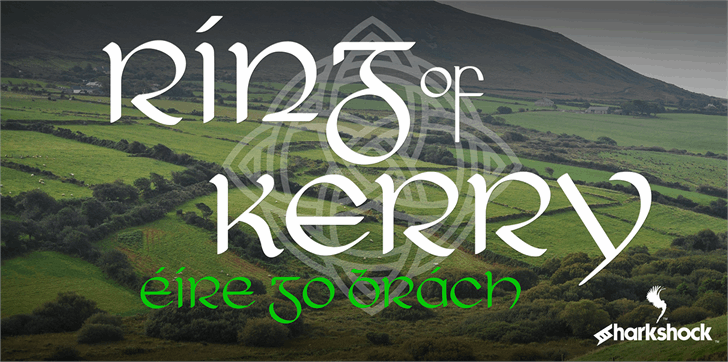
Ring of Kerry Font
A Ring of Kerry é uma fonte display vibrante criada pelo designer Hamilton, disponível tanto em formato OTF quanto TTF. Nascida em 2016, essa fonte exibe um toque alegre e dinâmico que encaixa-se perfeitamente para aplicativos de design gráfico como logotipos e publicações. Com uma paleta de cores vivas e detalhes impressionantes, Ring of Kerry oferece um tom vibrante que adiciona um charme visual único a qualquer projeto. As linhas levemente onduladas e os traços distintivos fazem dela uma escolha popular para designers de sites responsivos ou criação de materiais digitais em geral. Sem dúvida, essa fonte é um atalho elegante que certamente impressionará seus espectadores.